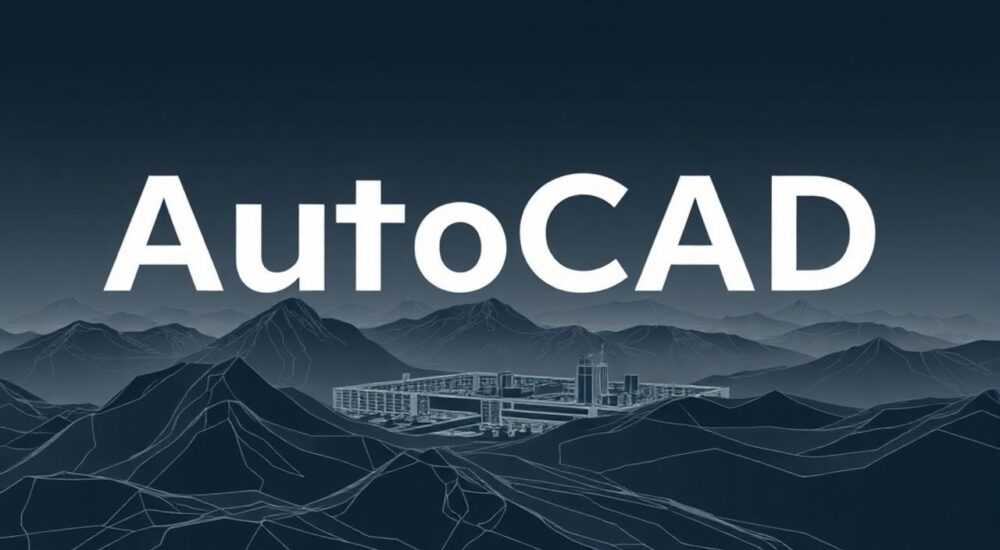
Шрифты в автокаде где лежат
Когда вы работаете в AutoCAD и сталкиваетесь с проблемой: шрифт не отображается, текст выглядит искажённо, или при открытии чертежа на другом компьютере появляются сообщения о нехватке шрифтов — чаще всего причина кроется не в ошибке программы, а в неправильной настройке или отсутствии файлов шрифтов в нужных папках. Понимание структуры хранения и управления шрифтами в AutoCAD — ключ к стабильной работе с текстом, совместимости между версиями и избежанию сбоев при обмене чертежами. Это не просто технический нюанс — это фундаментальная основа профессионального черчения.
Где хранятся шрифты в AutoCAD
AutoCAD использует два основных типа шрифтов: собственные бинарные форматы .shx (Shape eXchange) и системные TrueType (.ttf). Каждый тип хранится в своей директории, и их смешивание — частая причина сбоев. Стандартные шрифты, включённые в установку AutoCAD, находятся в подпапке Fonts внутри основного каталога программы. Например, в AutoCAD 2026 этот путь выглядит так: C:Program FilesAutodeskAutoCAD 2026Fonts. Именно туда программа обращается при открытии чертежей, если не найдёт нужный шрифт в текущем документе.
Помимо этого, AutoCAD ищет шрифты в папке Support — она расположена в той же директории, что и Fonts, но предназначена для пользовательских файлов конфигурации, шаблонов и дополнительных ресурсов. Если вы разрабатываете кастомные шрифты или используете сторонние библиотеки, их рекомендуется помещать именно в Support, чтобы не нарушать целостность установки. AutoCAD автоматически сканирует обе папки при запуске, но приоритет имеет папка Fonts.
Также стоит учитывать, что AutoCAD может использовать переменную среды FONTALT — она указывает альтернативный путь к шрифтам. Проверить её можно через команду OP → вкладка «Система» → «Пути к файлам» → «Альтернативный шрифт». Если здесь задан путь — AutoCAD будет искать несуществующие шрифты в этой директории, а не в стандартной.
Типы шрифтов в AutoCAD: SHX vs TTF
В AutoCAD используются два принципиально разных типа шрифтов, и понимание их различий критично для корректной работы.
Файлы с расширением .shx — это бинарные шрифты, созданные Autodesk специально для CAD-систем. Они компактны, быстро загружаются и обеспечивают стабильное отображение даже на слабых системах. Классические примеры: txt.shx (простой текстовый), gdt.shx (для геометрических допусков), romans.shx (классический ансамблевый шрифт). Они не поддерживают кириллицу в стандартной версии, но существуют расширенные версии, например, cp1251.shx или isocp.shx, адаптированные под русский язык.
Файлы .ttf (TrueType Font) — это системные шрифты Windows, такие как Arial, Times New Roman, Calibri. Они поддерживают Unicode, кириллицу, жирный/курсивный стиль и сложные символы. Однако AutoCAD загружает их медленнее, и при открытии чертежа на компьютере без этих шрифтов — текст может заменяться на шрифт по умолчанию.
Тип шрифта | Расширение | Поддержка кириллицы | Скорость загрузки | Гибкость стилей | Рекомендуется для |
SHX | .shx | Только специальные версии | Высокая | Ограниченная | Чертежи, стандартные надписи, ГОСТ |
TTF | .ttf | Полная | Средняя | Высокая | Технические документы, пояснения, печать |
- Определите тип шрифта: если это .shx — копируйте в папку
FontsAutoCAD. Если .ttf — копируйте вC:WindowsFonts. - Для .shx: откройте проводник, перейдите в папку установки AutoCAD → Fonts. Скопируйте файл туда. Не переименовывайте его без необходимости — имена шрифтов чувствительны к регистру и пробелам.
- Для .ttf: откройте папку
C:WindowsFonts(можно через Панель управления → Шрифты). Перетащите файл туда — Windows автоматически установит его. - Перезапустите AutoCAD — без перезапуска шрифт не будет доступен в списке.
- Проверьте доступность: откройте команду
STYLE→ в списке «Шрифт» появится ваш шрифт. Выберите его и примените к тексту.
Support — это может быть временный файл, а не полноценный шрифт.После установки шрифта можно создать новый стиль текста: введите команду STYLE, нажмите «Создать», укажите имя, выберите новый шрифт, задайте высоту (например, 3.5 для стандартных надписей) и нажмите «Применить». Теперь все новые тексты будут использовать этот стиль.
Частые ошибки и как их исправить
Самая распространённая проблема — при открытии чертежа появляется окно с сообщением: «Файл шрифта не найден: XYZ.shx». Это происходит, когда чертёж создан на другом компьютере, где был установлен кастомный шрифт, а у вас его нет.
Что делать:
- Ошибка 1: Шрифт не отображается — проверьте, лежит ли файл в правильной папке. Не в «My Documents», не в «Desktop» — только в